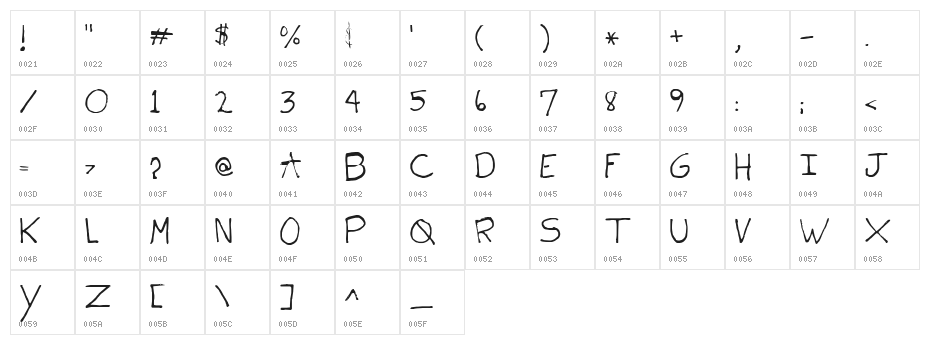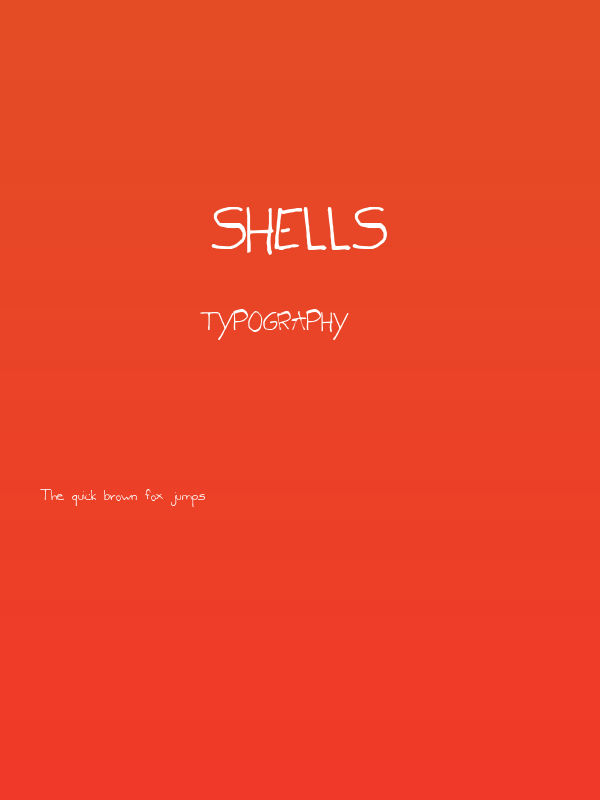
shells Font
✎ Handwritten
| 分类 | Handwritten |
| 整体风格 | Casual, Playful |
| 使用场景 | Headlines, Informal text, Creative projects |
| 推荐项目 | Ideal for greeting cards, children's books, casual invitations, and personal branding. |